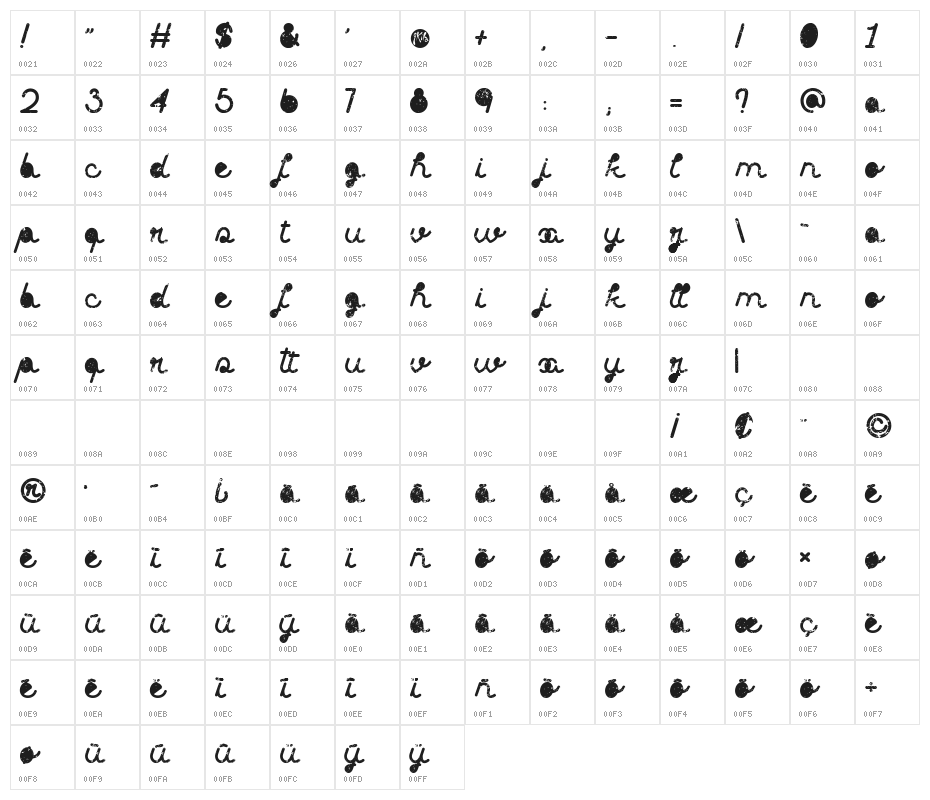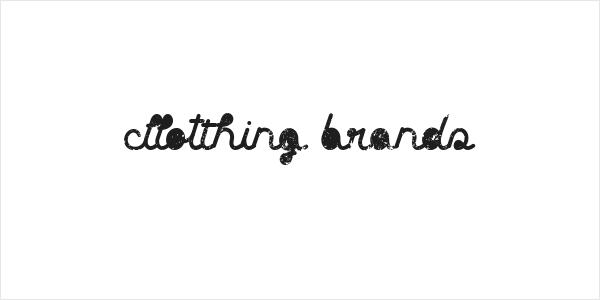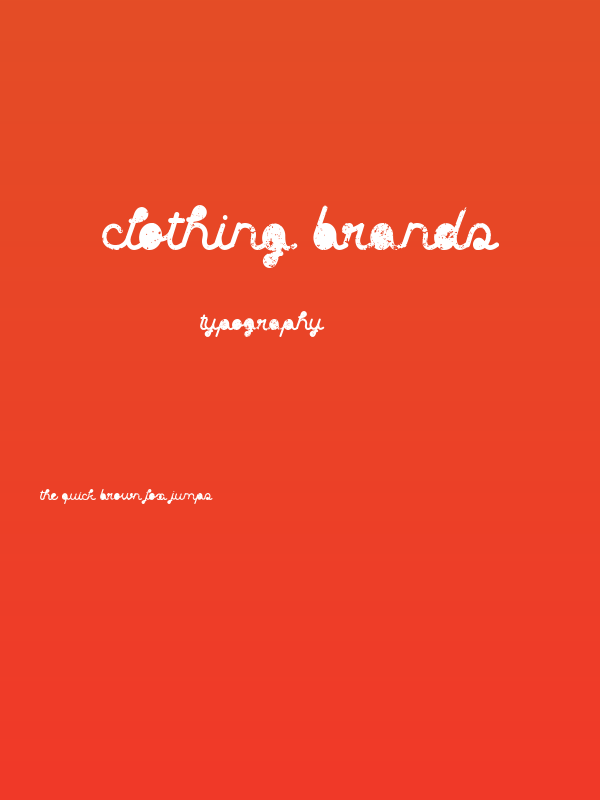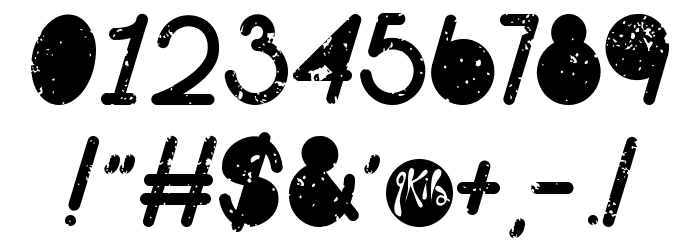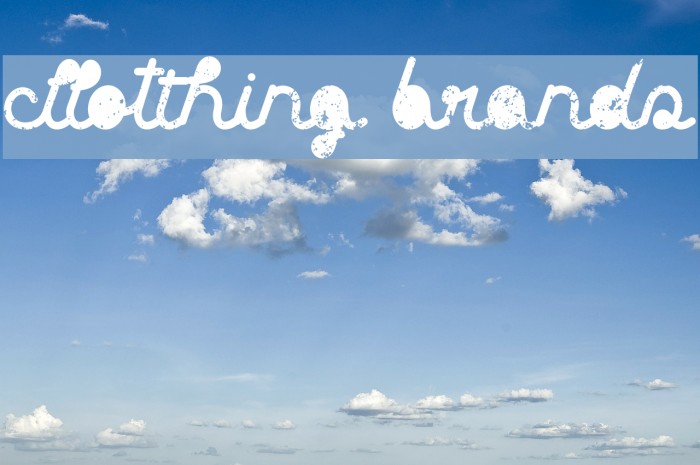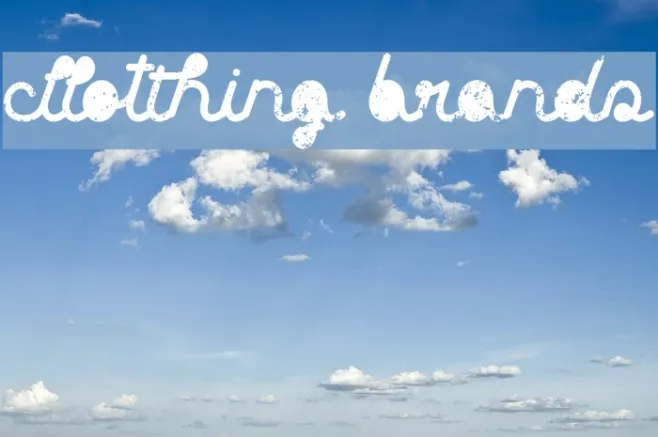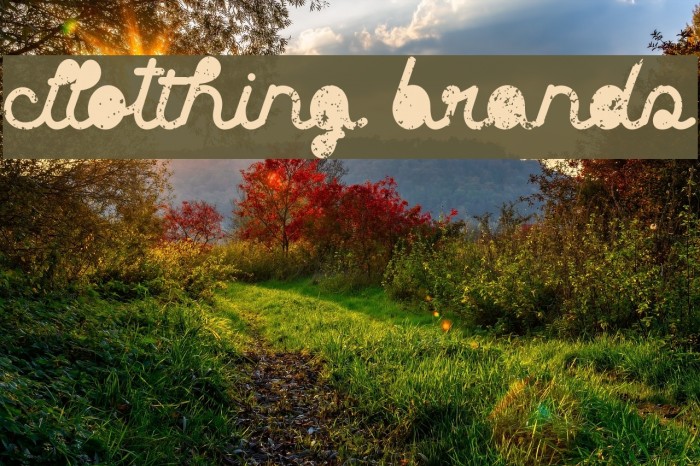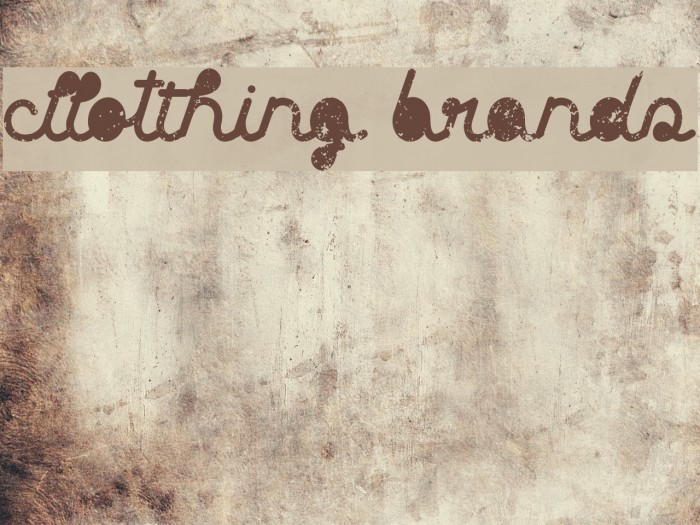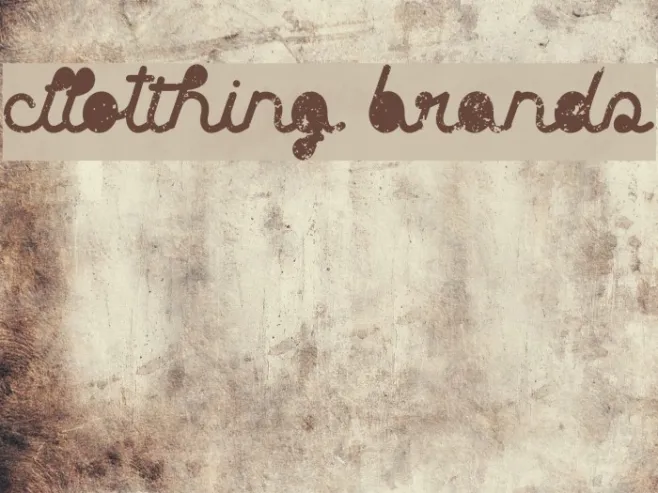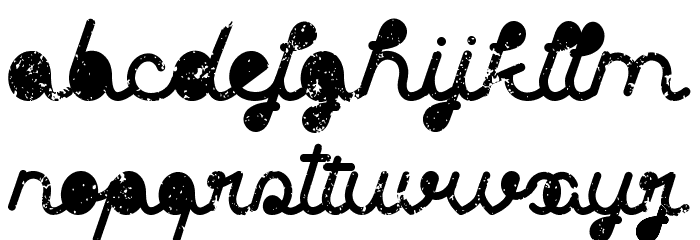
Clothing brands Font
| Estilo general | Vintage |
| Caso de uso | Logos, Posters, Album covers |
| Proyectos propuestos | Ideal for clothing brand logos, edgy posters, album covers, or any project needing a vintage, rugged look. |